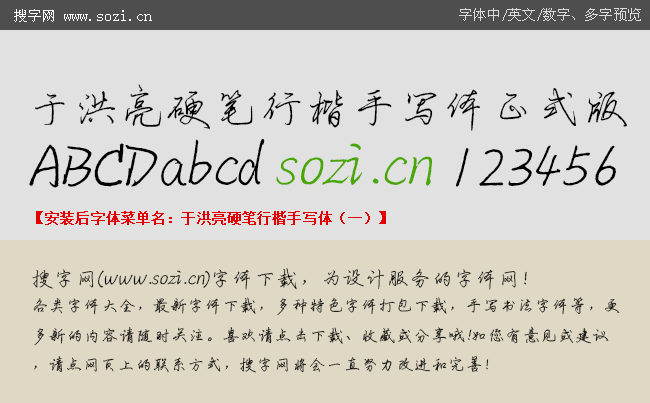
于洪亮硬筆行楷手寫體正式版
搜字網(wǎng)提供一款于洪亮硬筆行楷手寫體正式版中文書法字體下載,于洪亮硬筆行楷手寫體正式版是一款手寫風(fēng)格的鋼筆書法字體,字體書寫流暢,字形大方,整體效果十分出色,適合應(yīng)用于廣告設(shè)計(jì)、名片設(shè)計(jì)、包裝印刷、產(chǎn)品設(shè)計(jì)等應(yīng)用。